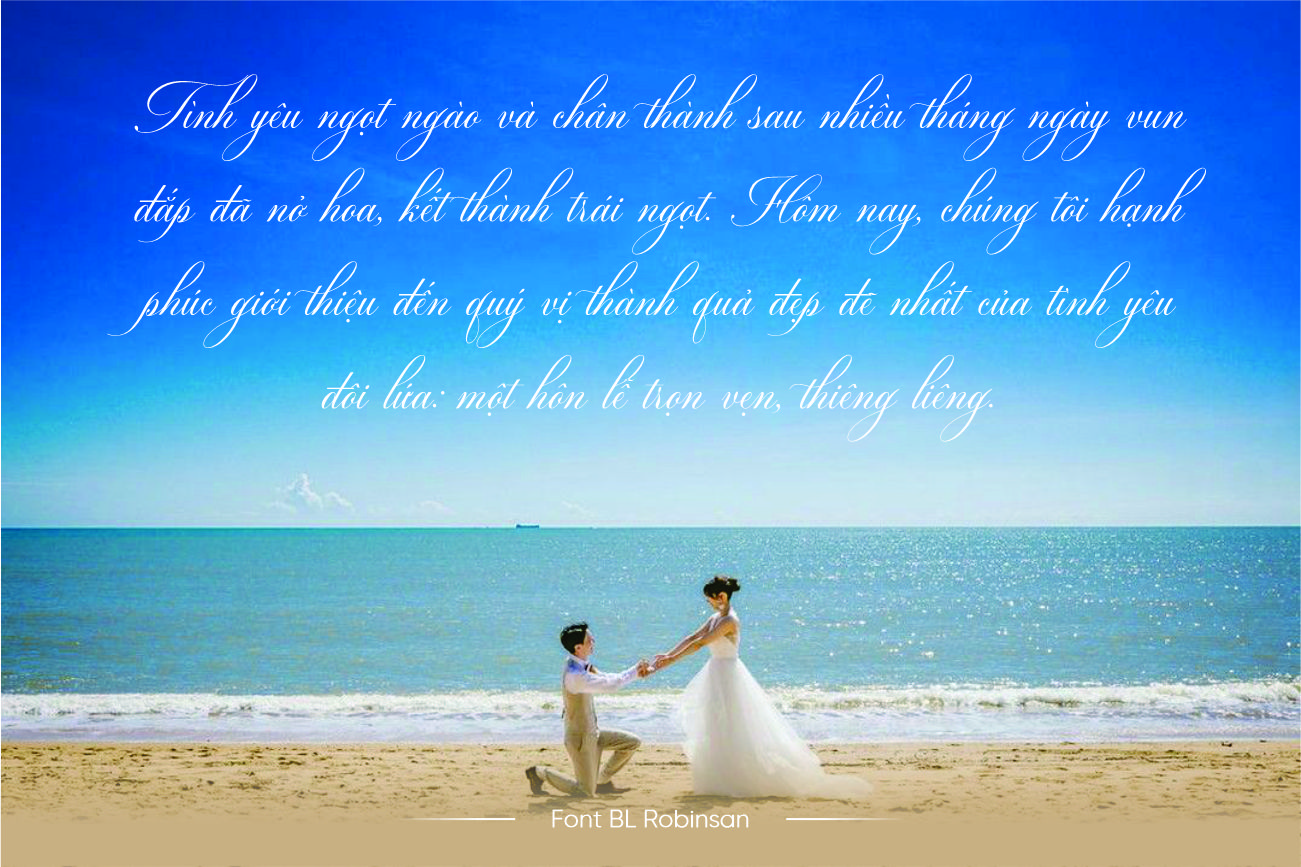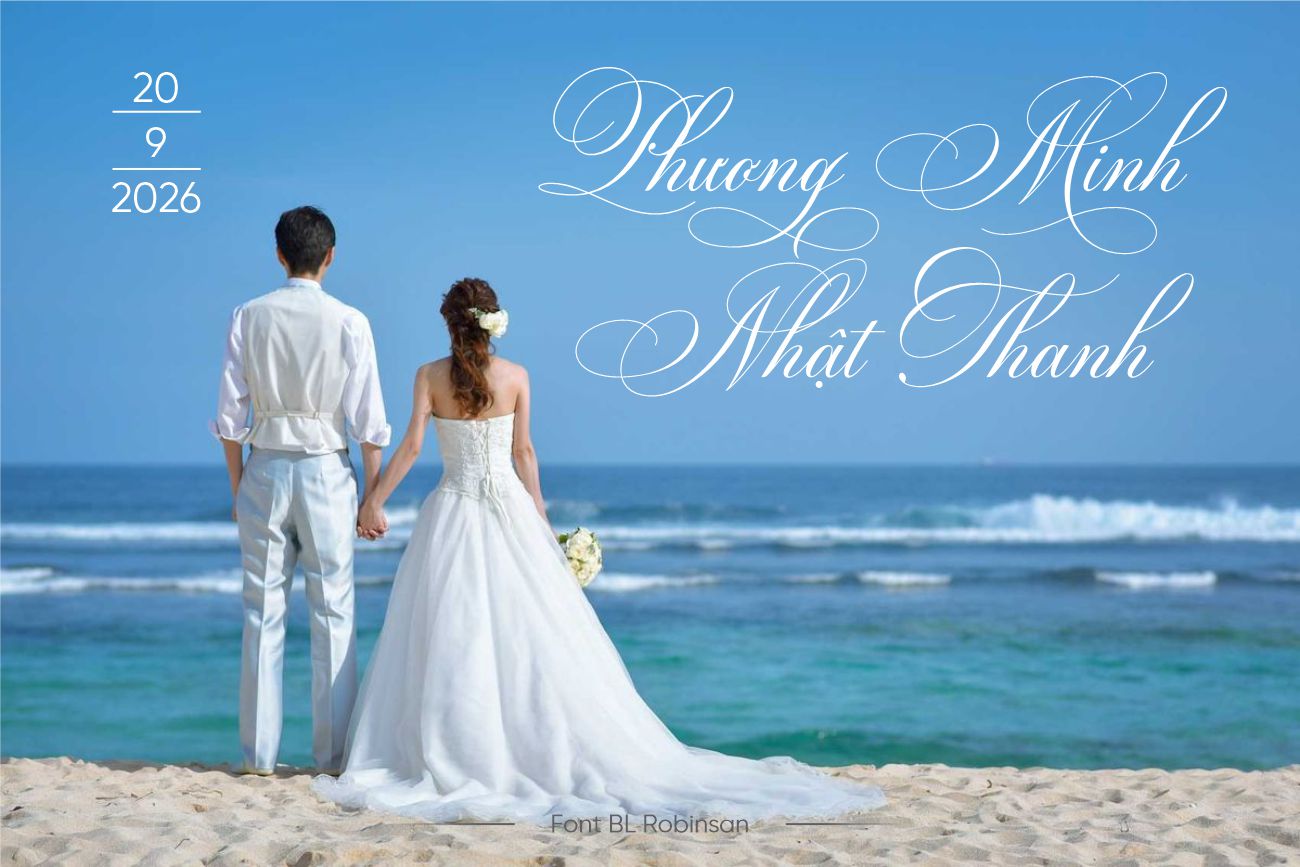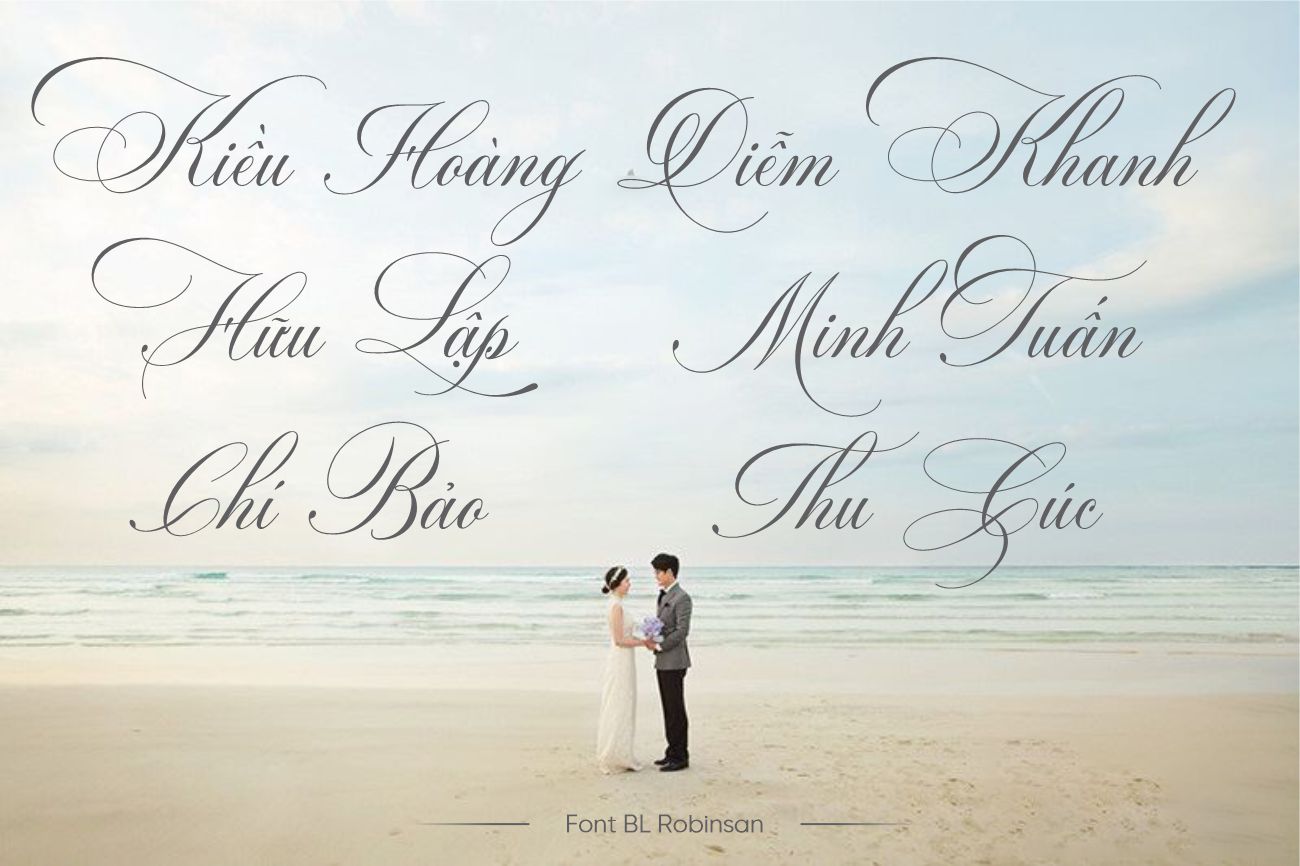
BL Robinsan
Font BL Robinsan là một kiểu chữ script hiện đại mang phong cách mềm mại và tinh tế, được thiết kế để tạo cảm giác gần gũi, bay bổng nhưng vẫn giữ được sự sang trọng.
Đặc điểm nổi bật:
Nét chữ uốn lượn tự nhiên, giống chữ viết tay với những đường cong mềm mượt.
Có nét thanh – đậm rõ ràng, giúp chữ vừa duyên dáng vừa dễ đọc.
Thích hợp cho các thiết kế cần sự lãng mạn và nghệ thuật, như thiệp cưới, bìa sách, poster hoặc logo mang tính cá nhân.
Hỗ trợ nhiều ký tự đặc biệt và ligature, giúp chữ ghép liền mạch, tạo cảm giác uyển chuyển.
Ứng dụng:
Font BL Robinsan thường được dùng trong:
Thiệp mời cưới, thiệp chúc mừng
Logo thương hiệu mỹ phẩm, thời trang, trang sức
Trích dẫn, typography nghệ thuật
Bao bì sản phẩm thủ công, handmade
Có thể xem BL Robinsan như một lựa chọn lý tưởng nếu bạn muốn mang vào thiết kế sự ngọt ngào, thanh lịch nhưng vẫn tự nhiên.